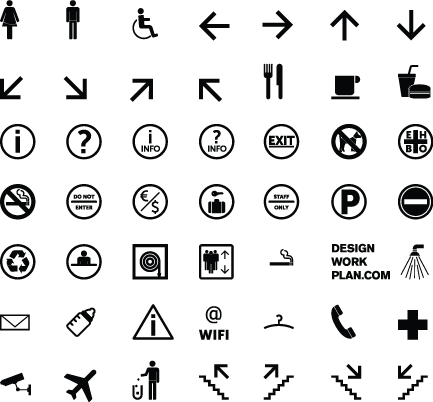
freier Open Type Font  Symbol Signs mit 50 Symbolen
freier Open Type Font  Symbol Signs mit 50 Symbolen – Für Anwendungen in Restaurants, Caffees, Toiletten, Museen, Universitäten, Schulen, Informationen, Services usw. …